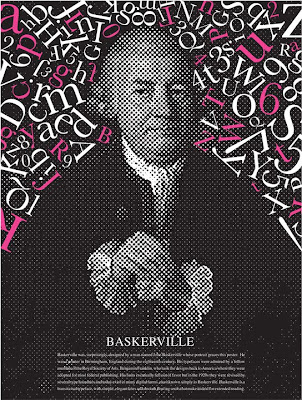
John Baskerville (Wolverley, Worcestershire, Inglaterra, 28 de enero de 1706 – 8 de enero de 1775) fue un impresor, miembro de la Royal Society of Arts. Dirigió a su pupilo John Handy en el diseño de numerosas fuentes tipográficas.
Se cree que Sir Arthur Conan Doyle, quien vivió en Birmingham, pudo haber tomado prestado su nombre para uno de sus relatos de Sherlock Holmes, El sabueso de los Baskerville.
Dotado de una gran delicadeza, elegancia y claridad en el diseño de tipos y composición de las páginas. La excelente calidad de sus impresiones influyó a grandes tipógrafos como Didot o Bodoni. Sin embargo, después de su muerte, sus tipos permanecieron desconocidos durante más de 150 años, hasta que Bruce Rogers, un diseñador norteamericano, los rescató, reeditándolos para Monotype en 1924 y Linotype en 1931.
El tipo Baskerville posee unas proporciones generosas. La mayor diferencia entre esta y las tipografías anteriores radica en una mayor diferencia entre los palos finos y gruesos. Se trata de una tipografía legible y clara, muy apropiada para libros de texto.